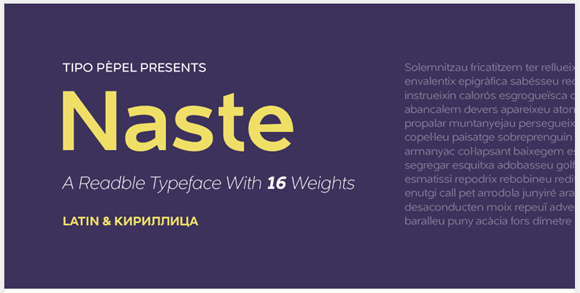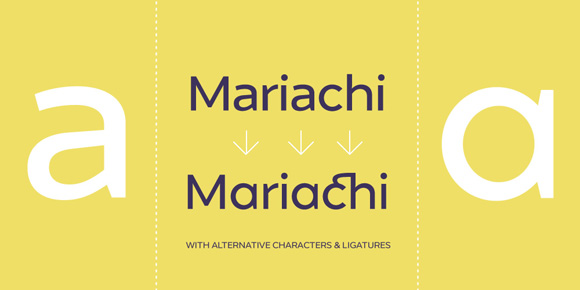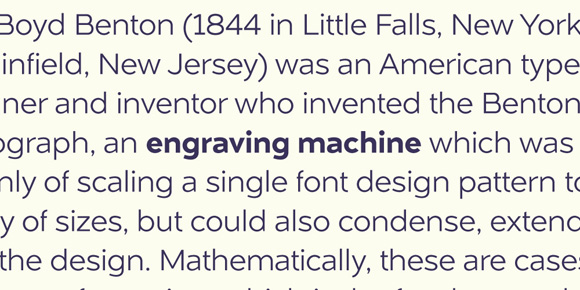
El prolífico Pep Patau no para e igual que llega el otoño y con el las setas, todos sabemo que en cuantos nos descuidemos Pep se nos va a presentar con una nueva tipografía. En este caso se trata de un «palo seco» de corte geométrico cuyas características principales nos comenta el gran Txus Marcano:
Tipo Pèpel ataca de nuevo con un exuberante derroche en formas y medidas, formas geométricas puras y básicas, aquellas que inspiraron a Paul Renner su celebérrima «Futura», uno de los mayores hitos del diseño tipográfico. Aquí se revisita unas formas clásicas para ponerlas al día, con infinidad de detalles que harán las delicias de los usuarios como las colas largas en las formas minúsculas cursivas que rompen la linealidad que se le supondría a una fuente puramente geométrica.
Hay otros muchos detalles ocultos en cada carácter de cada peso que le dan vigor y ritmo, alejando «Naste» de la tan manida sobriedad germánica geométrica, lo que ayuda a que su uso en la creación de jerarquías tipográficas basadas en la diferencia de la mancha tipográfica sea satisfactorio y fácil, gracias en parte a los muchos pesos disponibles y en parte a los muchos y muy cuidados detalles. Excelentes resultados con mínimo esfuerzo. Ancha en la altura de «x», contenida en las ascendentes y descendentes; gruesa pero elegante, de fácil lectura y necesitada de blancos generosos donde mostrar sus encantos. Más es mejor que menos.
Y como ya es habitual en Tipo Pépel, los más completos juegos de alternativas Opentype disponibles, así como soporte Unicode para 104 idiomas además del cirílico. 16 pesos de hermosura tipográfica en todo su esplendor.